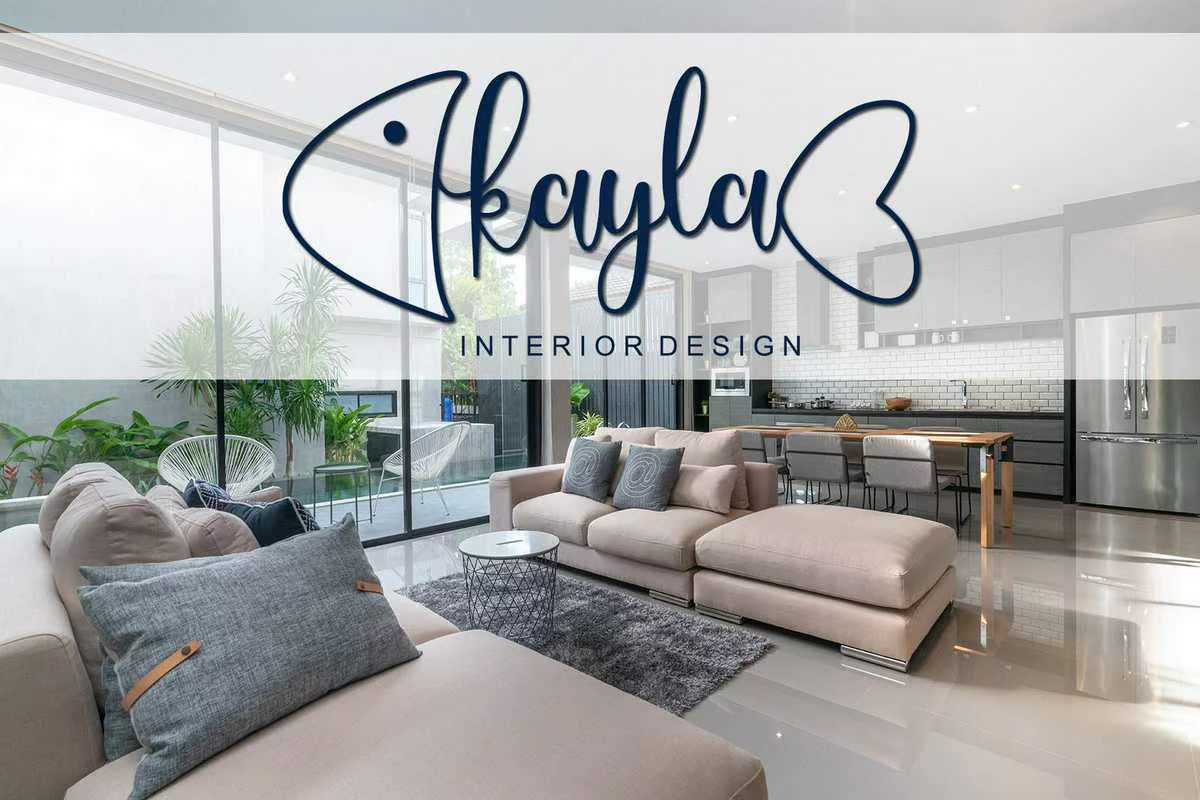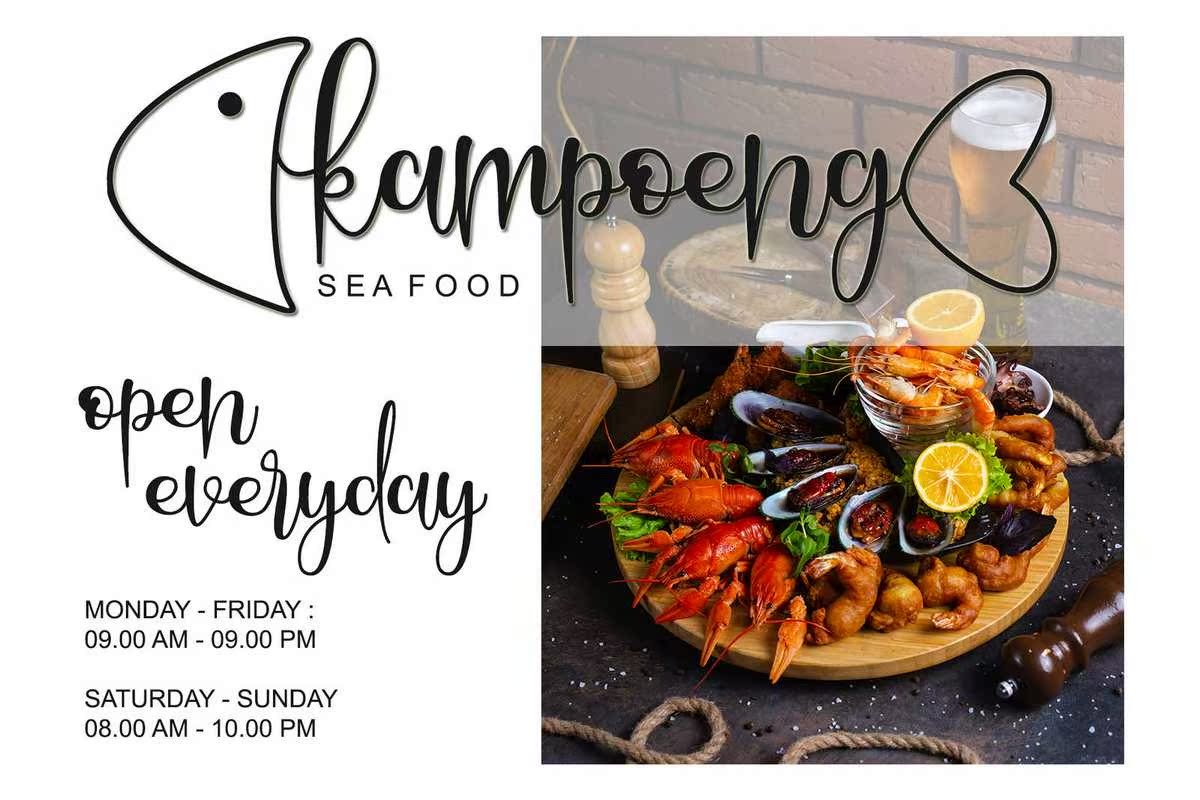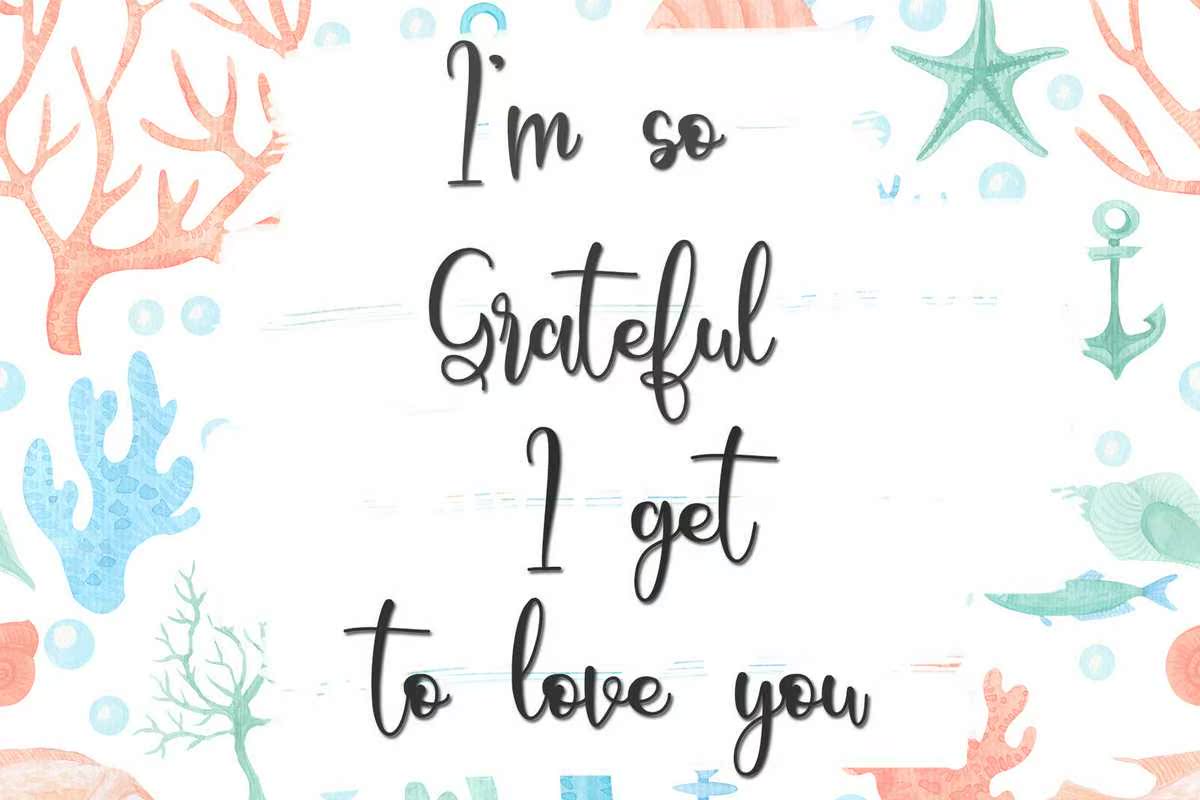
FishBoneFontSamodernCalligraphyFontBylettRafaStudio.It具有流动字母,可让您的设计与FihModel.FishBoneFontPerfect保持一致;徽标、问候卡、包装设计、耐磨性、工艺设计、任何项目、书名、婚礼宣传、包装等。FishBoneFontByletterRafaStudio.Ithas Flowing Letters将为您的设计提供符合FihModel.FishBoneFontPerfect的流动字母;徽标、问候卡、包装设计、耐磨性、工艺设计、任何项目、书名、婚礼宣传、包装等。